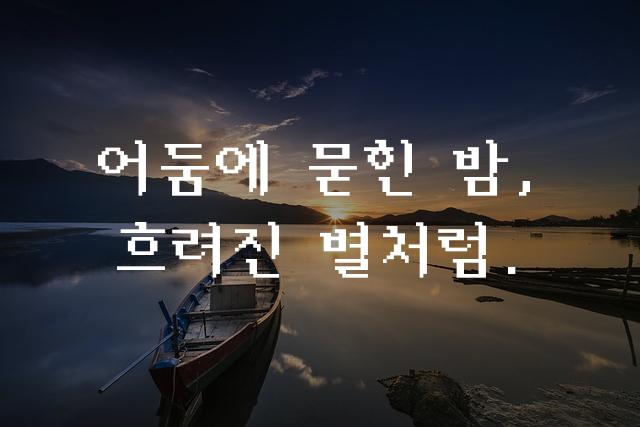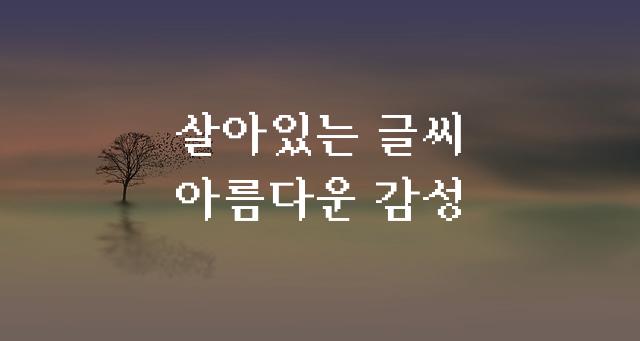
‘도스한글’은 이민서 제작사에서 제작한 기본 고딕 폰트로, 깔끔하고 현대적인 디자인을 자랑합니다. 이 폰트는 한글 타이포그래피의 기본을 충실히 따르면서도, 간결하고 명확한 라인이 특징입니다.
도스한글은(는)
기본 고딕, 감성적인, 부드러움 계열의 생김새를 가지고 있으며
로고 디자인, 광고 캠페인, 브랜딩 등에서 자주 활용되며, 효과적인 메시지 전달에 적합합니다.
이 폰트는 광고/마케팅, 크리에이티브, 소매/유통 분야에 잘 어울리며,
명확한, 창의적인, 전문적인 느낌을 담고 있는 것이 특징입니다.
이 폰트와 유사한 폰트로는 나눔고딕, 말리부고딕, 제네바 등이 있어요. 함께 비교해 보시면 좋습니다!